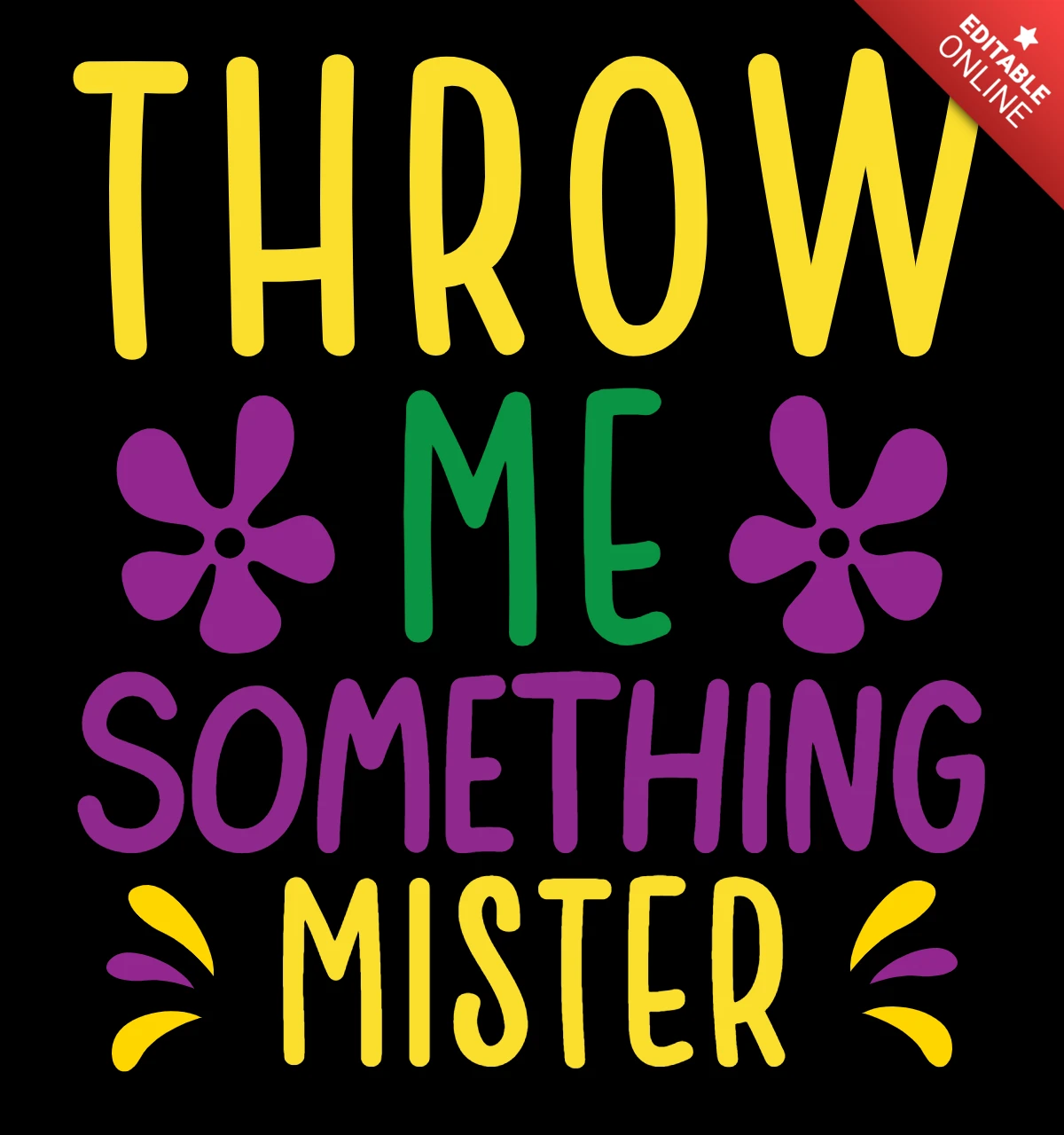
Modèle de typographie festive et colorée : "throw me something mister" (lancez-moi quelque chose, monsieur)
Éditer dans Design Studio Télécharger en JPGCréez des vêtements et des affiches éclatants grâce à nos modèles colorés ! Parfaite pour mardi gras, notre typographie festive capture l'esprit du carnaval : "Lancez-moi quelque chose, monsieur !